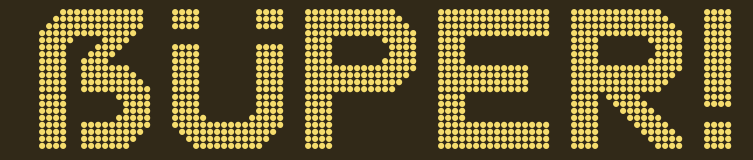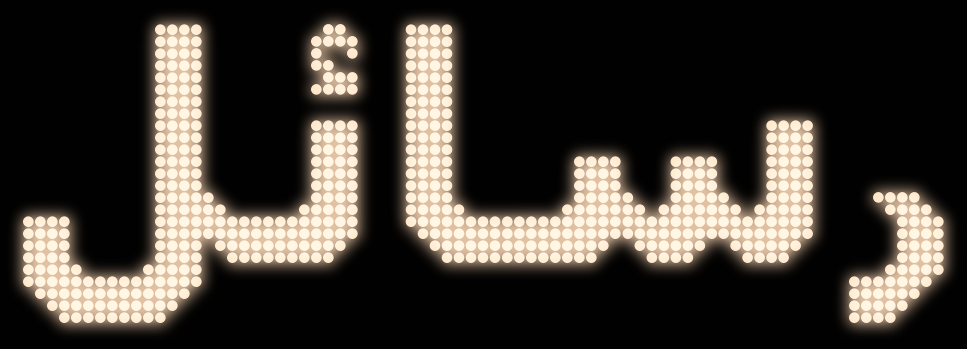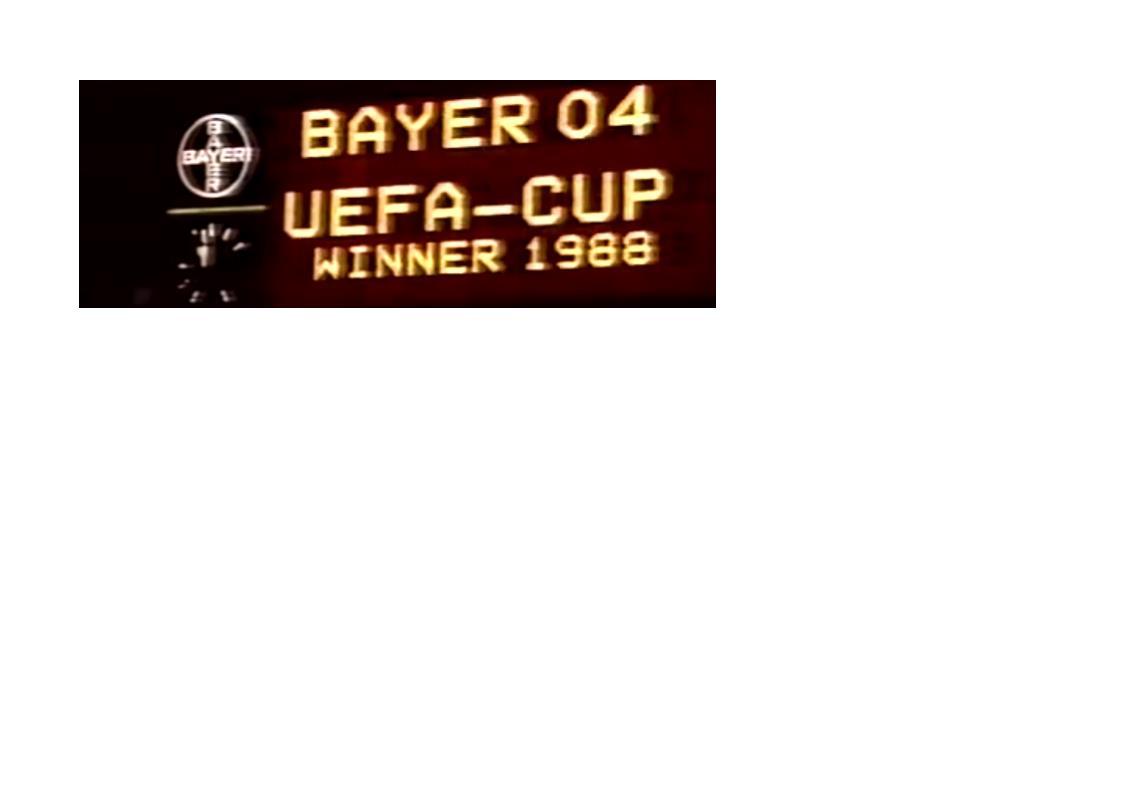
Suche alte Schriftart der Anzeigetafeln aus den Stadien
Ich bin für meinen Neffen auf der Suche nach der Schriftart die Ihr auf dem Bild sehen könnt! (Bild aus 05/1988)
Ich vermute das es sich um eine "Standard-Anzeigetafeln-Schrift" handelt , da ich Sie in dern neunzigern mehrfach gesehen habe!
Habt ihre eine Idee wie diese genau heißen könnte? Im Olympiastdion München war Sie damals auch zu sehen.
Da die Schrift aus vielen Lampen besteht, kannst Du bei Pixelschriften glücklich werden. Exakt diese Schrift wird es nicht als Font geben, da das Verhältnis von Lampe zu Tafel und dergleichen doch sehr speziell sind.
Hey, das ist doch diese gräßliche Siemens-Schrift die man in vielen Bussen und U-Bahnen sieht, oder?! Ne, damit darf ich ihm nicht ankommen, danke dir trotzdem 🙂
Matrixanzeige war übrigens das Wort, was mir fehlte 🙂
Hey, ich dachte es wäre eine eigene Schriftart gewesen, da ab Mitte der Neunziger ja auch einige Stadien Arial oder Times als Font verwendeten.  Er möchte gerne mit seinem Freund das Stadion nachbauen und dabei auch die Anzeigetafel mit diesem Slogan versehen, einfach drucken reichte dem jungen Mann nicht 😄
Bei den Schriften werden die Buchstaben auch aus anderen Segmenten zusammengesetzt. Bei der Stadionschrift ist das ein Punktraster.
Mit der Zeit wurden betreffenden Lampen immer besser, was Größe und Leuchtstärke anbelangte. Bald waren ja auch Farben möglich. Der Anfang wurde jedenfalls mit Glühlampen auf einem bestimmten (und ich vermute nicht standardisierten) Raster gemacht.
Hier findest Du einen ganzen Sack voller Punktmatrix-Schriften: https://www.myfonts.com/search/dot+matrix/
Du kannst sogar versuchen, das Buchstabenraster auszuzählen, wenn Du ein entsprechend gut aufgelöstes Photo hast. Es gibt für viele Anzeigezwecke schon fertige Schriften, deren Raster offengelegt wurde (4*8 beispielsweise: vier Punkte breit, acht hoch).
Sehr wahrscheinlich wird die Schrift nicht einmal einen Namen gehabt haben, und wird in der Anzeigesoftware wohl so etwa 18 x 24 heißen, also die Zeilen und Spalten für einen Buchstaben.
Ich habe in meiner Schriftenbastler-Laufbahn auch mal so eine für ein Zeichensatz-ROM eines Messgerätes programmiert. Das war auf Karopapier zeichnen, dann den Zeilen die Bytes zuweisen ( buchstänlich auszählen), und dann die ganzen Spalten im Hex-Editor eingeben, das erste Byte war der ASCII-Code der Glyphe, das 2. Byie die Zahl der Spalten für eine Glyphe incl Leerraum, dann der genaue Bitcode für jede Spalte, jeweils aus 2x 8 Bit (was bedeutet, die Zeichen hatten, zusammen mit "Durchschuss" 16 Zeilen). eine 1 bedeutete da dunklen Punkt drucken, eine 0 weiß lassen, bzw. bei der Stadion-Anzeige 1 = Lampe an, 0 = Lampe aus.
Heute funktioniert es ja mit deutlich höherer Auflösung mit den Standard-5mm LEDs, die jetzt einen echten Video/Computerbildschirm bilden, und daher den Einsatz eines normalen Fonts ermöglichen.
Aber wenn du dir schon die Mühe gemacht hast, Kyrillisch und Griechisch einzubauen, kriegen wir dann auch noch lateinische Diakritika? :biglove:Mich jiepert es ja besonders nach ÁÉÍÓÚŐŰ für Ungarisch. Dann könnte Þorstelinchens Website auch dreisprachige Anzeigebanner haben.
OK, auch erledigt. Aber polytonisch Griechisch mache ich hier nicht - auch bei noch so viel lieb guck...
Hehe, ich glaube nicht, dass solche Schriften jemals polytonisch geschrieben wurden :)
Sicher??? Schließlich waren es die alten Griechen die Olympia und Amphitheater erfunden haben und da muss es ja auch irgendwelche Anzeigetafeln gegeben haben. :hammer:
Etwa so:
Man stellt eine große Holztafel auf, darin ist ein Raster aus regelmäßigen Löchern gebohrt. Die Löcher sind mit Pergament abgedeckt. Hinter jedem Loch ist eine feder belastete Klappe angeordnet, an die dann jeweils für die Fläche eines Buchstabens Fäden befestigt sind, die, zieht man daran die Klappen für den jeweiligen Buchstaben öffnen. Hinter der Vorrichtung ist ein Spiegel,der Sonnenlicht von Hinten auf die Anzeigetafel lenkt. Die Punkte des Buchstabens leuchten dann.
Und da die Fäden mit dem Finger gezogen wurden, nannte man diese Anzeigen digital...
und mich jiepert es ein wenig nach
Nur leider habe ich es in Fontlab 5.2 noch nicht hinbekommen,das der Font in Arabisch auch Rechts nach Links funktioniert.